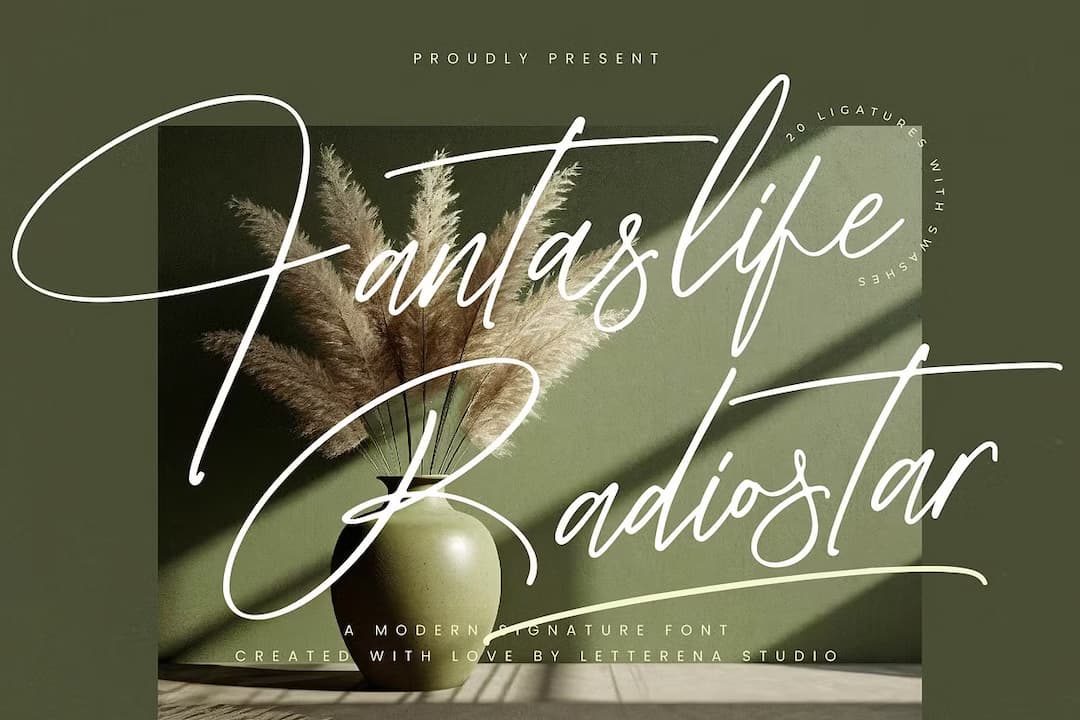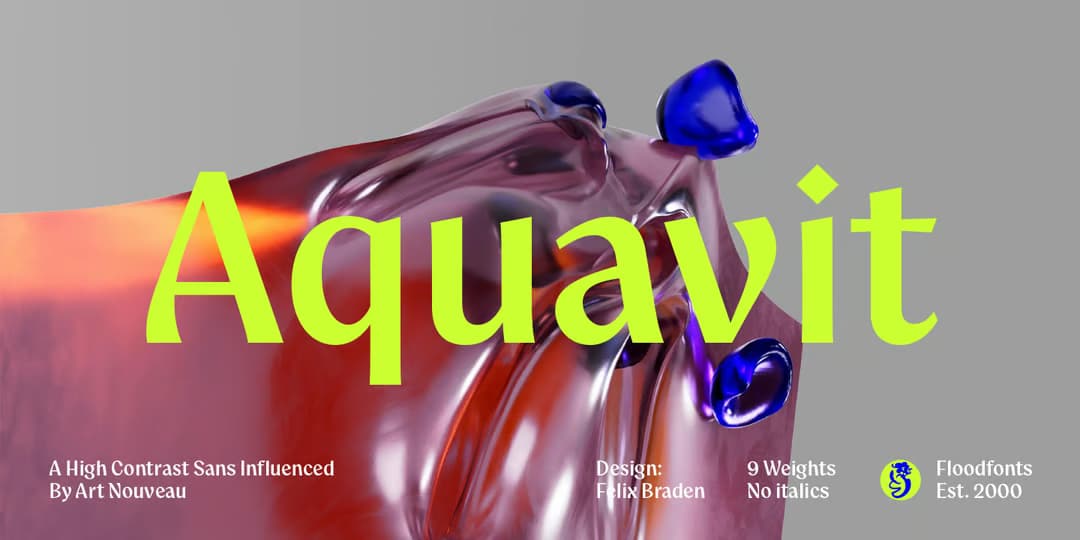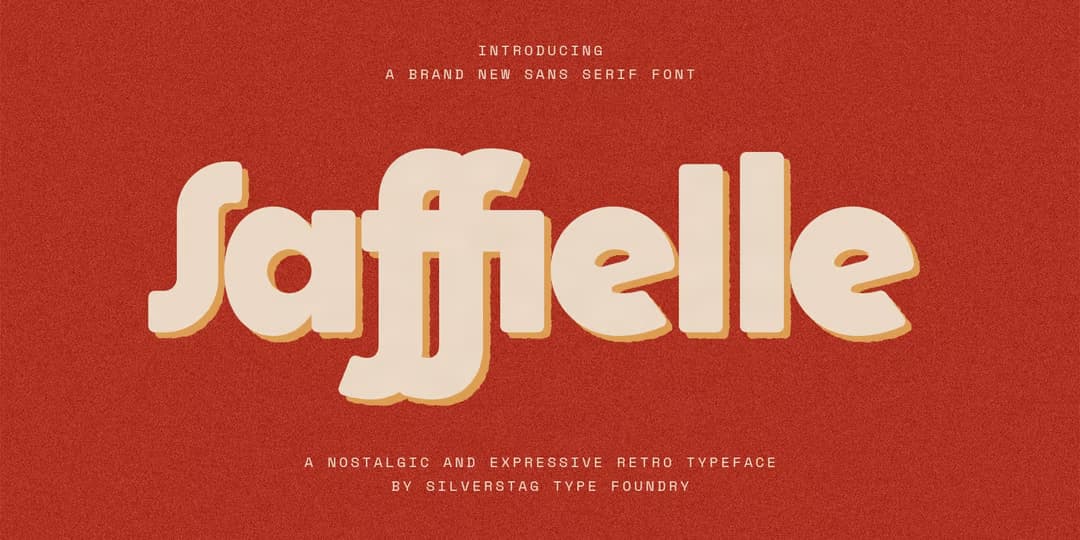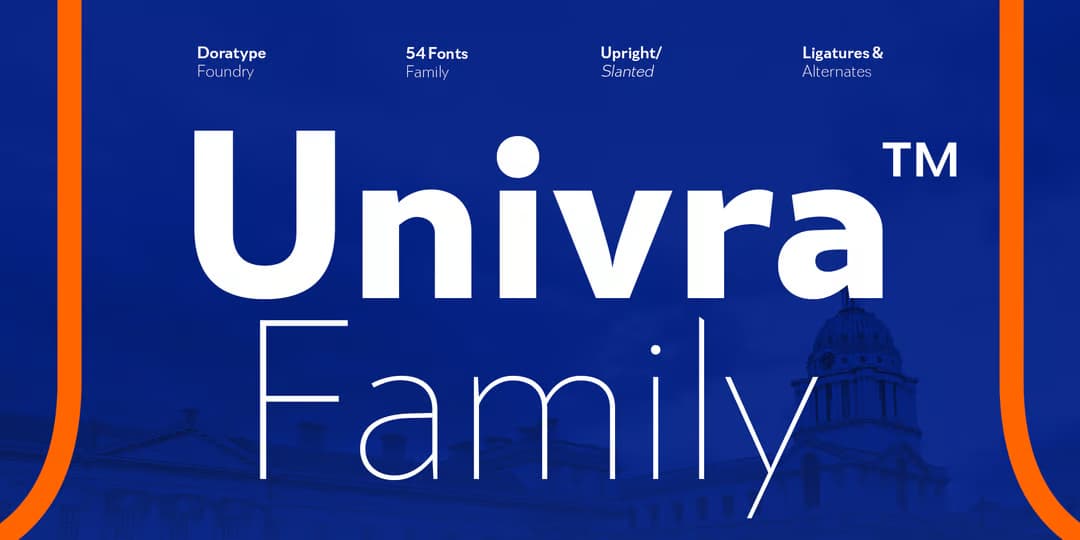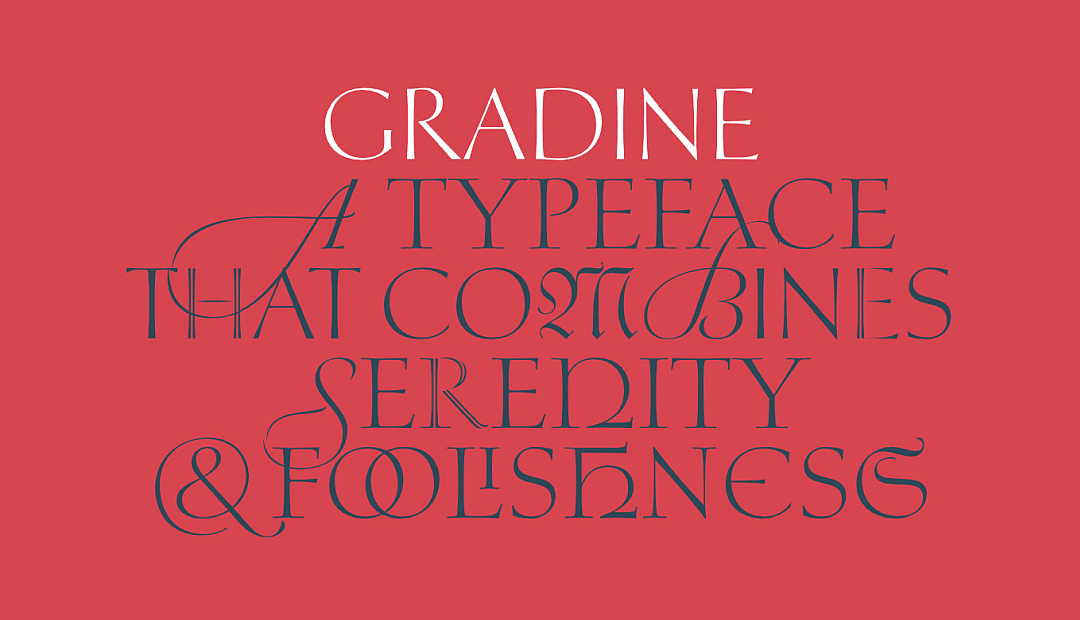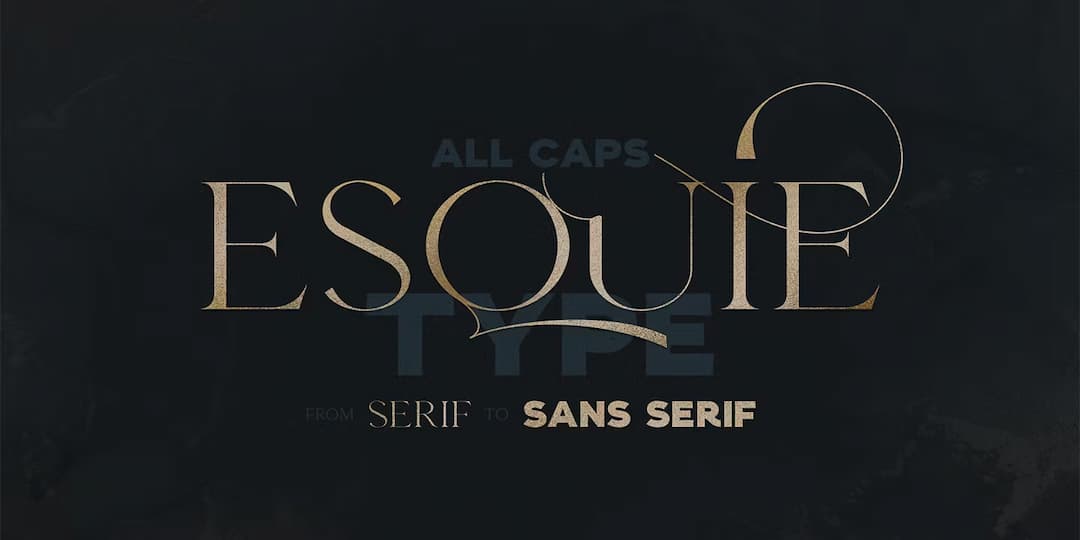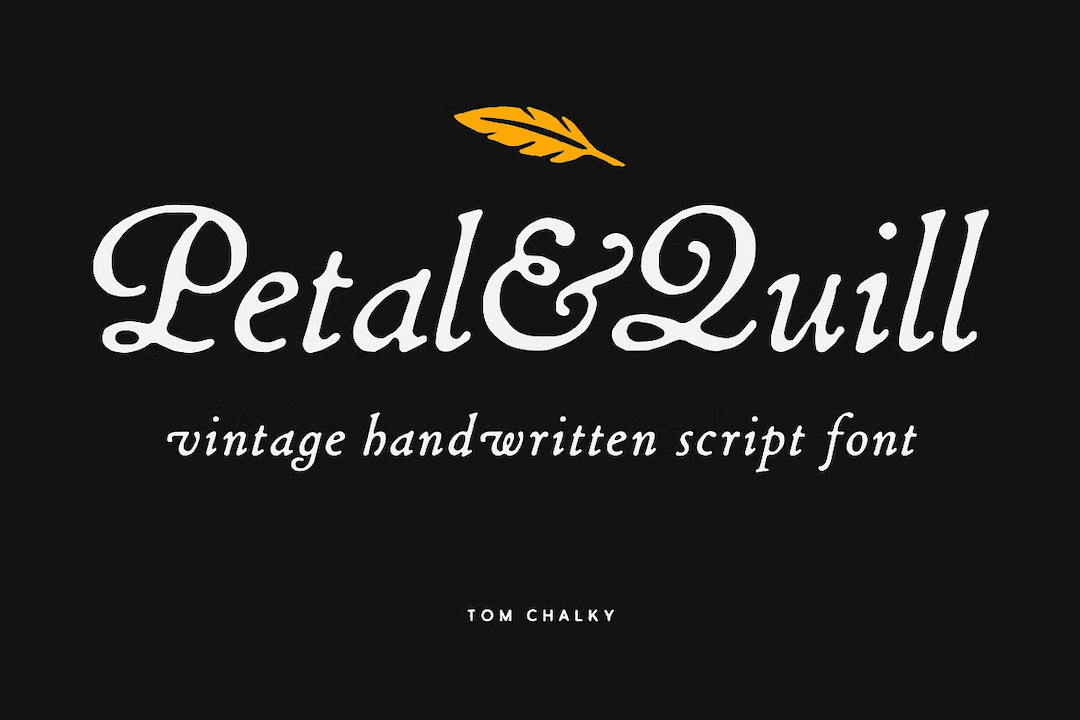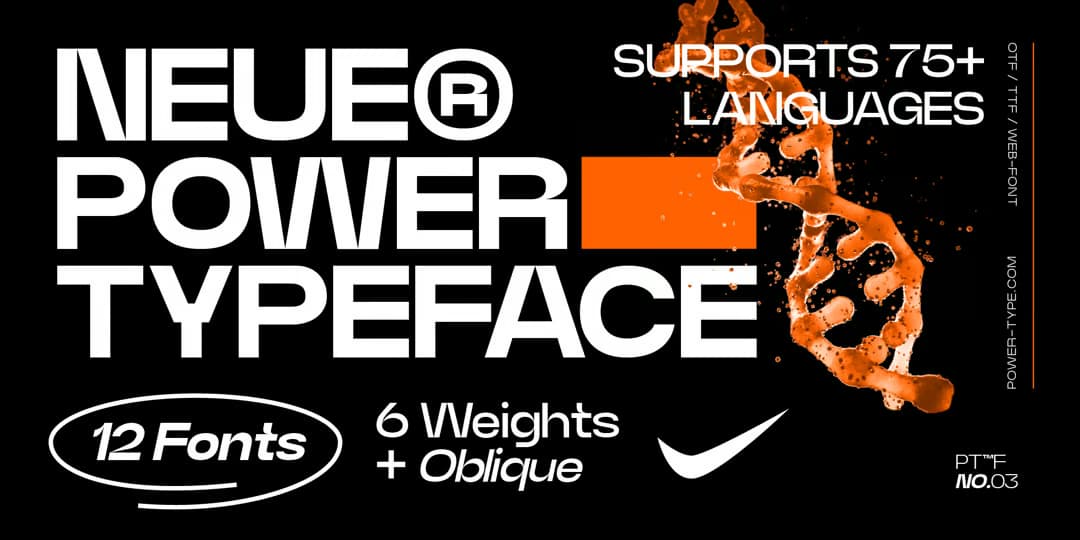
ダイナミックながら読みやすいシグネチャースクリプト。素早くややコントラストの付いたストロークで書かれており、大文字は見ての通り結構ダイナミックだが、小文字はグリフがさほど崩れておらず可読性は良好。F が筆記体特有の逆向きなのが読みづらいが、大文字さえ読めればなさほど苦も無く判読できる使い勝手の良い書体だろう。大文字にはオルタネートがないが、小文字にはリガチャーが少々。大きな t を含んだリガチャーが多数あって、スペルにあると目を引くアクセントになると思う。傾きの強い Italic と2スタイル。
オーガニックなサンセリフディスプレイ。ややカリグラフィー風味のあるグリフとストロークをしているサンセリフで、作者はアール・ヌーヴォーの風味を取り入れているとしているが、あんまそうは見えない(笑)。まあほんのりあるかな、という感じ。コントラストがあって不意に曲がるストロークが特徴的。可読性が良く、割と長文を組んでも読みやすい。名前はジャガイモが原料の北欧の蒸留酒のこと。語源はラテン語で「命の水」らしい。9ウェイト。
レトロポップなサンセリフディスプレイ。図太くてアウトラインの角が丸くなった柔らかな印象の書体で、グリフはヴィンテージ感のあるやや古いスタイル。小文字の s がスクリプト型なのが特徴的。画像の S や f がイタリック風だがこれはオルタネートで、通常のグリフもちゃんとあるのでご安心を。アウトラインがスムースな Regular と、細かく荒れた Vintage の2種がある。1ウェイトのみ。
汎用性の高い多目的サンセリフ。xハイトは高すぎず低すぎず、グリフも素直なスタンダードで可読性は程よい。とにかくニュートラルなので特筆すべき特徴もなく、何を書いていいのか分からない(笑)。文字幅がレギュラーの他に Condensed と Expanded と計3種あり、それらが Slanted もあって9ウェイトずつで合計54種とビッグファミリー。サインなんかに良さそう。
大変繊細で美しいディスプレイのミクスドファミリー。カリグラフィー要素を多分に含んだクラシカルで非常にエレガントな書体の集合体で、細めの Roman/Italic、フレアセリフ気味になった Sans/Sasn Italic、インラインが入った Incised Roman/Sans、アンシャル風味のグリフの Antiqua、フラクトゥール風味の Blackletter、カッパープレート風味の Script、アラビア文字の Arabic と、これらの書体に似合う Ornament がある。Roman と Sans には大文字のみのようだがギリシャ文字(Greek)とキリル文字(Cyrillic)もあり。計15種。作例は多種混ぜて組んでいるが、ウェイトが揃っているので特に違和感はない。どれもかなり筆者好みで非常に欲しい(高い…)。
ほぼ同じ骨格で様々なスタイルを持ったディスプレイ。画像はよくある繊細なモダンローマンディスプレイだが、実はこれ1種ではなく、図太いサンセリフとこのモダンローマンの間に7種、計9種のスタイルをグラデーションで持っている。画像のスタイルの Serif を始めとし、順に Soft Serif, Semi Serif, Hybrid, Modulated Sans, Humanist Sans, Neo Grotesque, Geometric Sans, Sans Serif となる。途中にヒューマニストやジオメトリックの名が見えるが、それぞれの名にふさわしい骨格に若干変化している。これをひとつにまとめたバリアブルタイプもあり。大文字のみ。
ヴィンテージ感あふれるイタリックディスプレイ。カリグラフィースクリプトっぽい大文字と活字イタリックっぽい小文字のセットで、アウトラインがインキが滲んだようにポタッとしていて古めかしい。xハイトが割と大きく、デコラティブなのは大文字だけなので結構読みやすい。オルタネートもないのでこの手としてはシンプルで素直な書体である。スタイルが2種あって、アウトラインがさらに滲んだ Round があり、それぞれに Bold と2ウェイトずつ。
ストロークが途切れ途切れになっている変わったサンセリフディスプレイ。画像の N, W, A などをご覧いただけば分かるようにストロークがぶつんと切れているヘンな書体で(失礼)、小文字の多くは R のボウルのように一部細くなる処理が施されている。全体的になんかちょっと違和感があり、それが目を引くおもしろいディスプレイとなっている。アップライトとオブリークの2スタイルで6ウェイト。本日はなかやまきんに君の誕生日(1978)らしい。パワー!
なんと Futura に新しい版が出た。2027年に Futura 誕生から100周年らしいのでそれを記念して制作された模様。オプティカルになっており、レギュラーと Text の2種あってそれぞれに Oblique があって6ウェイトずつとバリアブルタイプもあり。加えて「マルチスクリプト」の名の通り多言語対応となっており、ギリシャ文字やキリル文字はもちろん、アルメニア文字やアラビア文字、ヘブライ文字、ジョージア文字、ラーオ文字、タイ文字など現時点で12種類の文字があるが、2026年末までには簡体字やハングルまで含めて23種まで拡張するとの事。とんでもない一大プロジェクトである。予定に和文が見当たらないのが残念…ゴシックが得意な日本人デザイナーが手を挙げてくれる事を祈る。ジオメトリックな仮名…難しいか?